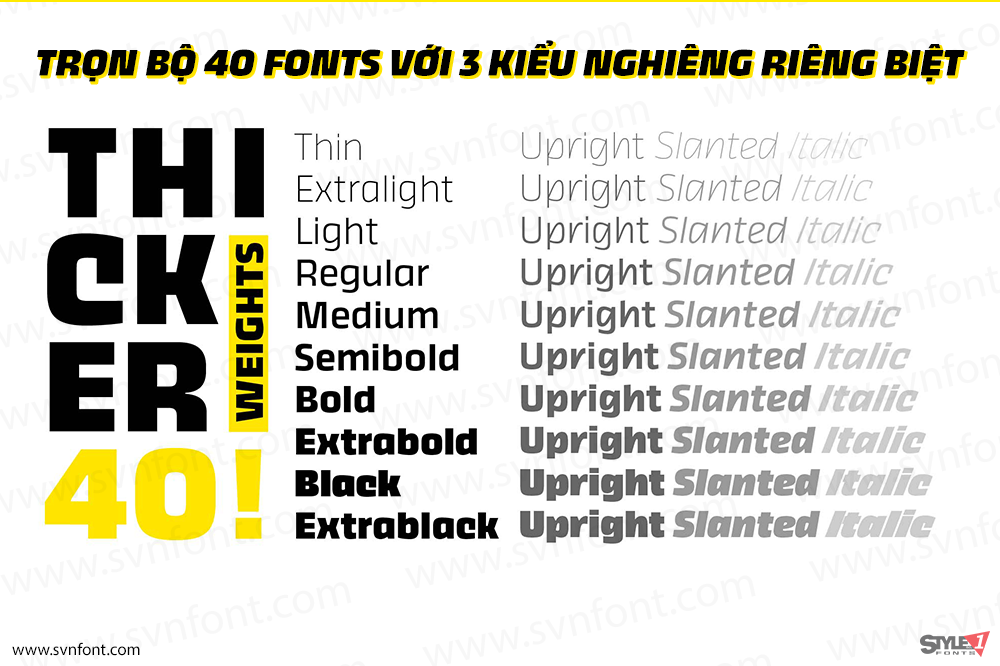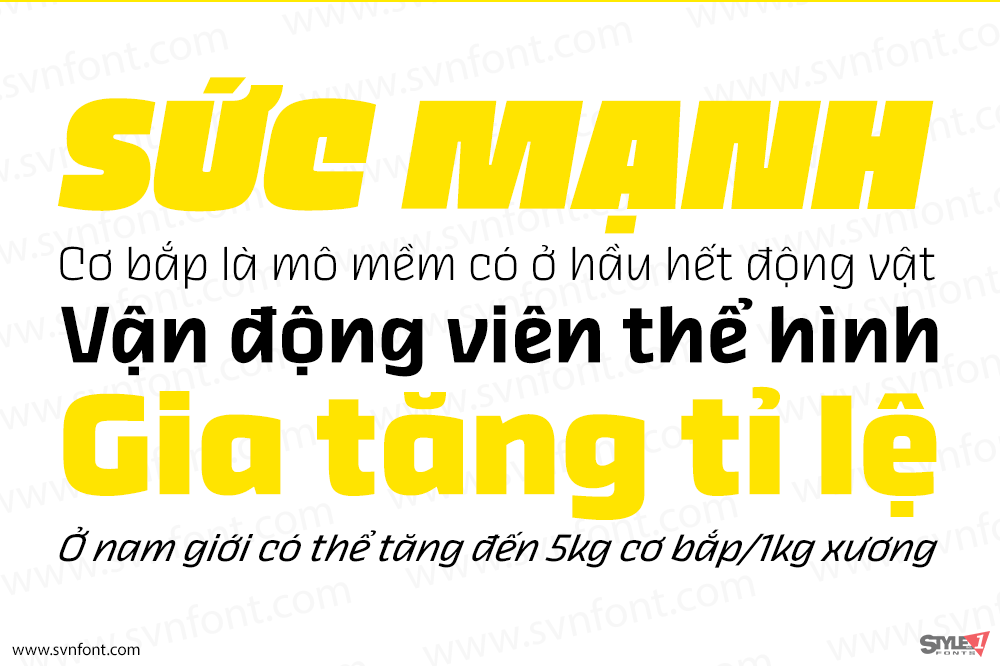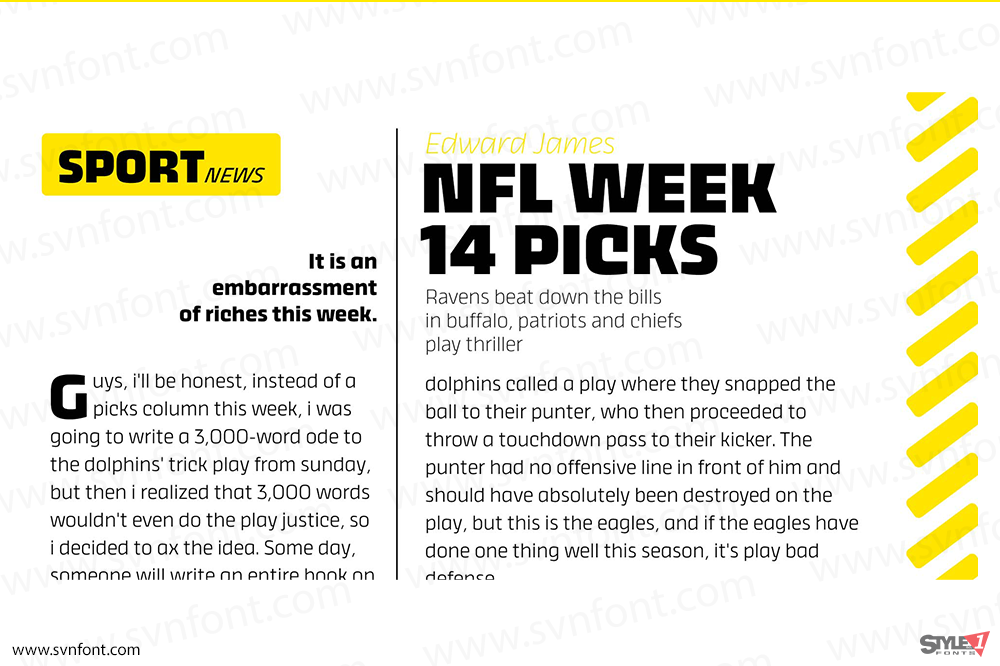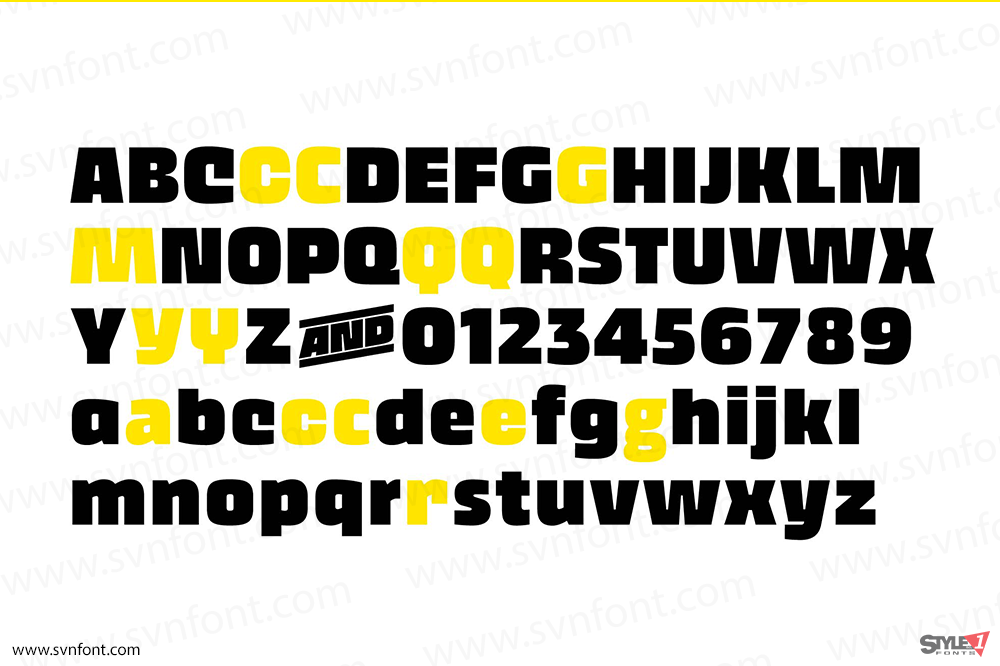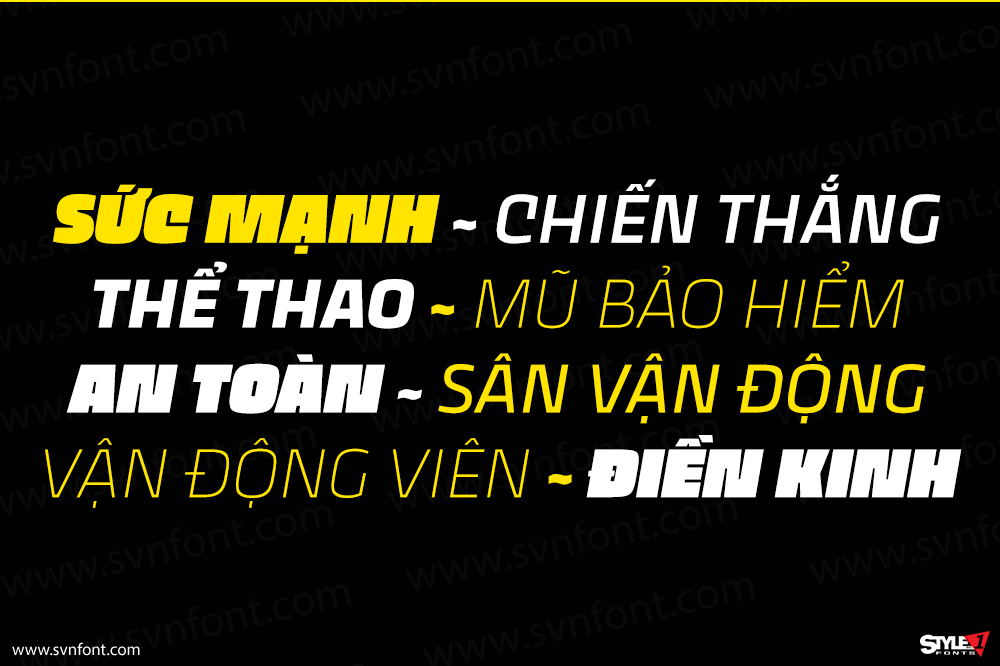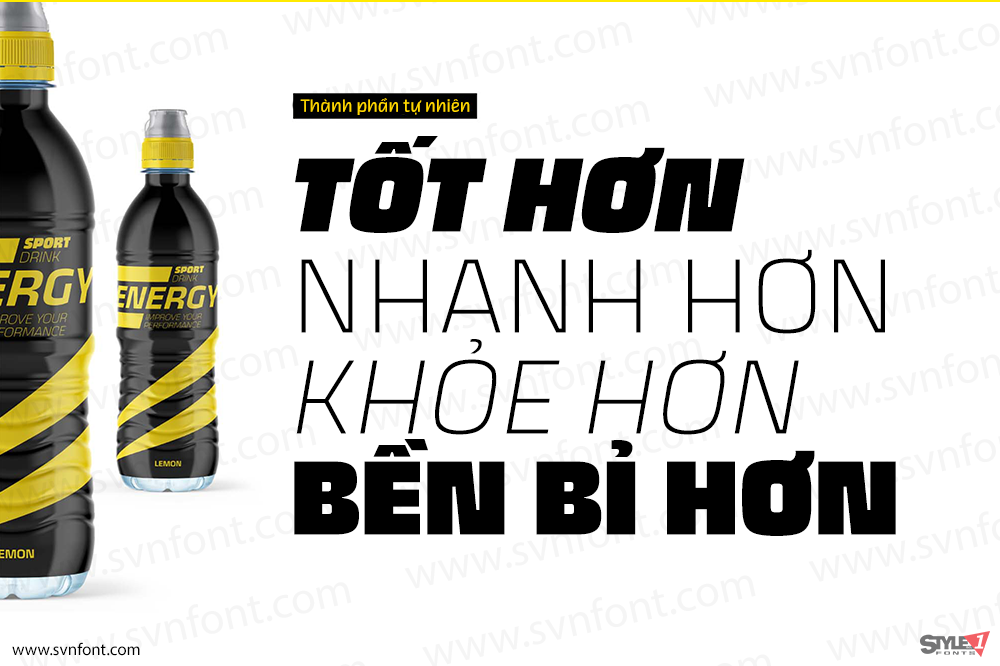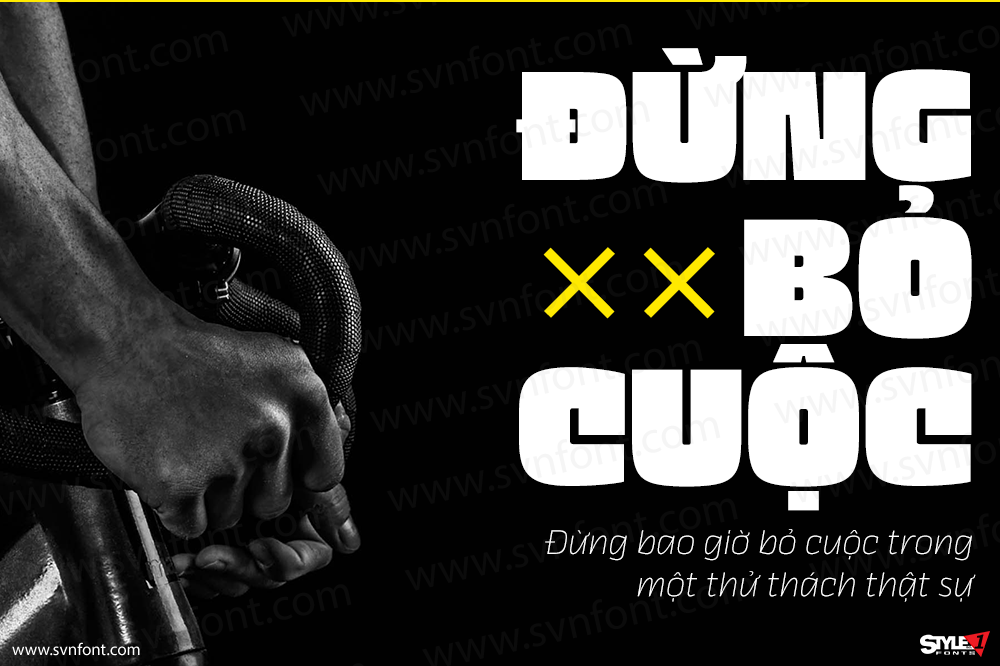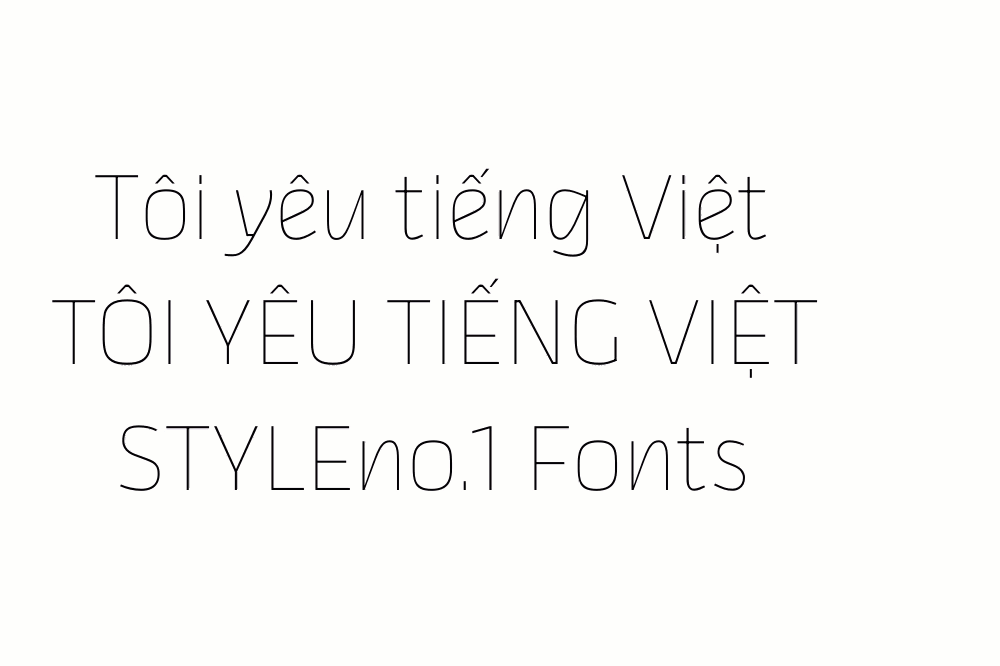
Thicker là một bộ font được Francesco Canovaro và Andrea Tartarelli thiết kế cho Zetafonts. Là một kiểu chữ sans serif hình học đầy mạnh mẽ, ban đầu nó được thiết kế với độ đậm cực đại (extrabold) mang tính thẩm mỹ của các kiểu chữ năng động, mạnh mẽ thường dùng trong truyền thông thể thao. Sau đó, nó được phát triển với các độ dày nhẹ hơn, nơi các hình dạng thể hiện tỷ lệ lấy cảm hứng từ phong cách cổ điển và vẻ ngoài hơi vuông vức, gợi nhớ đến Eurostile nổi tiếng của Novarese, đồng nghĩa với phong cách retro-futurism.
Với những ảnh hưởng đa dạng này, kiểu chữ cho phép sử dụng ấn tượng trong hiển thị và thiết kế logo hiệu quả, cũng như sử dụng tinh tế hơn trong các ấn phẩm văn bản – với khuynh hướng tự nhiên cho quảng cáo mạnh mẽ và hiệu quả. Các kiểu chữ thể thao thường sử dụng chữ nghiêng để tăng thêm sự năng động và tác động, và Thicker tuân thủ điều này bằng cách cung cấp lựa chọn ba dạng nghiêng thay thế với độ nghiêng khác nhau, được tùy chỉnh hơn nữa nhờ việc tích hợp công nghệ font biến đổi (variable font) cho phép tinh chỉnh dải độ dày cũng như lựa chọn chính xác độ nghiêng của kiểu chữ.
Trong mỗi 44 độ dày của bộ font (cũng như trong giải pháp font biến đổi tất cả trong một), Thicker cung cấp một bộ ký tự mở rộng với hơn 900 ký tự Latin, Cyrillic và Hy Lạp, bao gồm hơn hai trăm ngôn ngữ và các tính năng OpenType hữu ích (Các dạng thay thế, Số liệu vị trí, Chữ hoa nhỏ và Các dạng nhạy cảm chữ hoa/thường) để dàn trang hoàn hảo.
Nhà thiết kế: Francesco Canovaro, Andrea Tartarelli
Nhà phát hành: Zetafonts